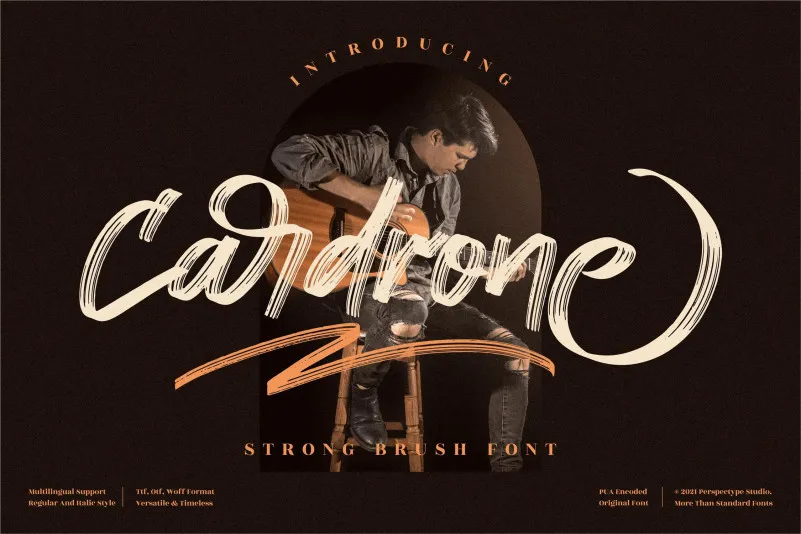
A Cardrone Font é uma opção única para quem busca um estilo elegante e sofisticado que se destaca na sua coleção de fontes. Este script círboolo, elaboradamente trabalhado e com detalhes meticulosamente incorporados, oferece o máximo em precisão e elegância. Seja ela utilizada em um design gráfico respeitoso ou em uma criação de layout editorial, a Cardrone Font é uma fonte que pode transformar qualquer projeto. Com sua natureza círboola e bold brush característica, essa font se destaca ao dar vida aos seus textos, destacando-se como um recurso indispensável no seu arsenal de recursos gráficos. É perfeita para aqueles que buscam uma escrita elegante e vibrante em suas criações.